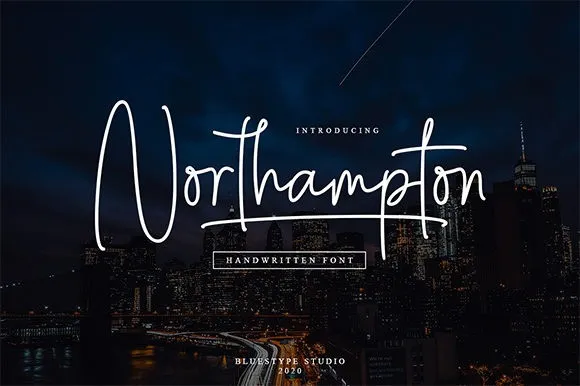
Introduzimos a Northampton Handwritten Font, uma fonte com traços manuscritos que imita a aparência e o estilo de notas ao acaso e esquisitas. Esta é uma opção perfeita para marcas de moda, sites comerciais, blogs de tendências ou qualquer negócio que deseje se apresentar com elegância e sofisticação. Nesta fonte criada pelo Bluestype Studio, a Northampton é um estilo de letra assinatura encantador com um toque interessante. Ela tem traços leves e divertidos, tornando-a perfeita para adicionar um toque pessoal a qualquer projeto gráfico. Ideal para uso em designs de moda, carteirinhas de negócios, convites de casamento, desenhos de camisetas, logotipos, citações, fotografia e muito mais.